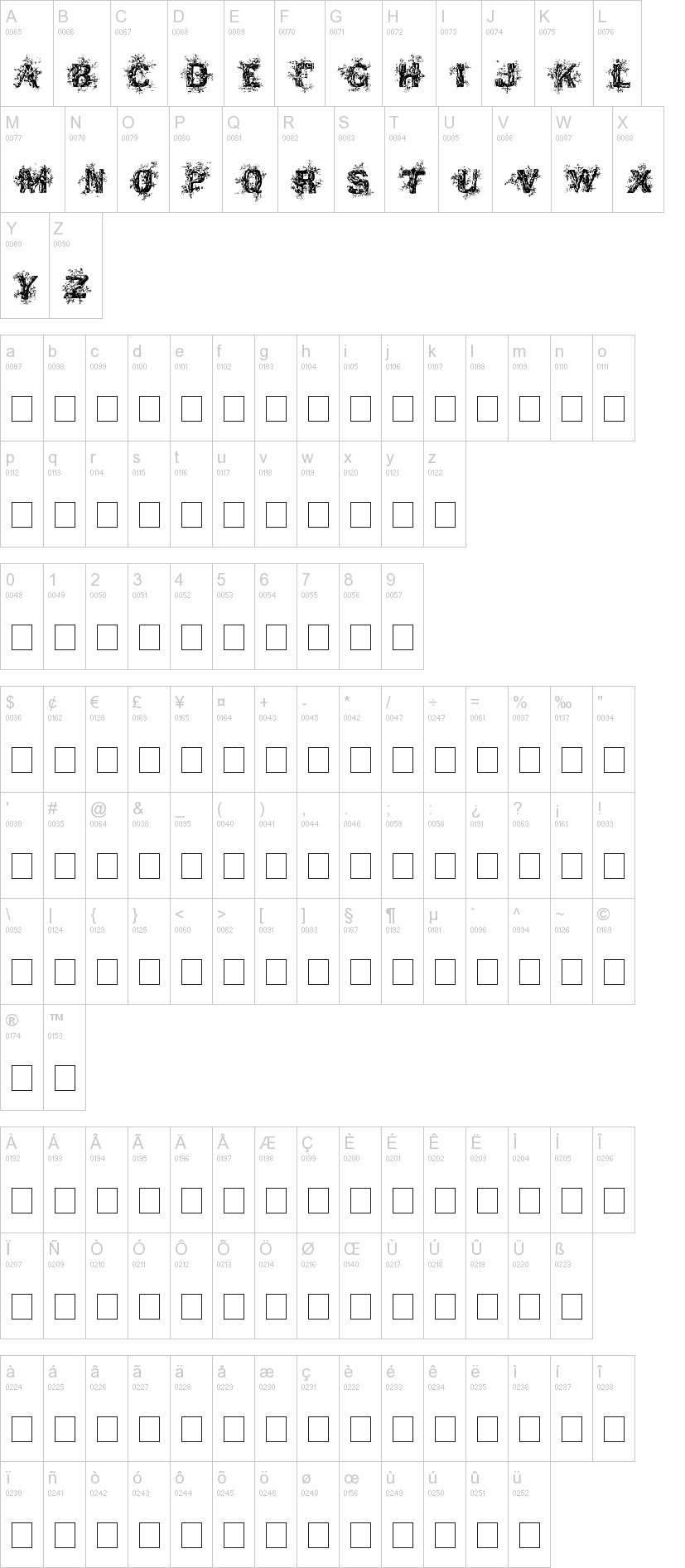
Deep Woods Initials 是一种非常独特的装饰性字体,它的设计灵感来自于深山森林中的手绘木刻字母。该字体设计师克里斯托弗·汉德曼(Christopher Hansen)将这种粗糙的手工风格融合到数字化设计中,从而创造出了这款极具特色的字体。 Deep Woods Initials 字体的特点在于每个字母都有一种粗重的线条,并带有一些手工刻痕和纹理效果,这种风格非常适合用于草原、森林或野外等大自然场景的设计。此外,这款字体还包含了一些特殊字符,例如手绘的箭头和其他装饰性元素,可以为设计带来更多的灵感和创意。 总之,Deep Woods Initials 是一款非常独特的字体,适合用于大自然、野外和探险等主题的设计。内容介绍
Deep Woods Initials是一款非常不错的手写艺术字体,具有很好的视觉感,适合于文化类的宣传设计、商业类品牌的广告和产品包装设计以及个性化文字排版等较多场景。